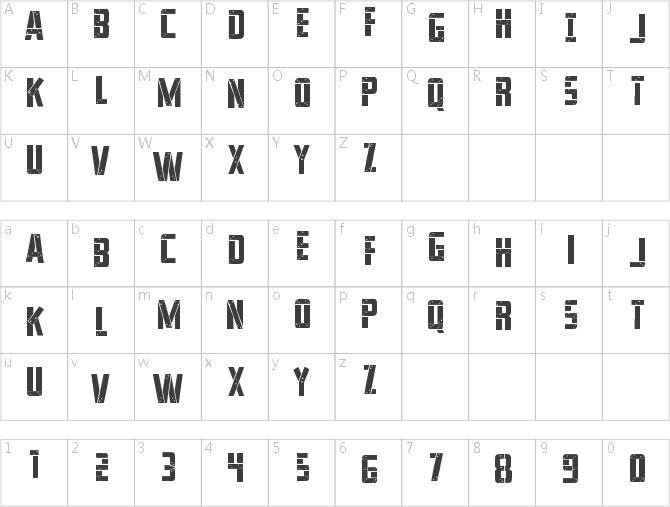
Frank-n-Plank Staggered 詳情頁
Frank-n-Plank Staggered
Frank-n-Plank Staggered介紹
Frank-n-Plank Staggered字體字庫是一款讓人賞心悅目、百看不厭的英文字體,適合各類廣告和產品包裝設計應用,字體大小0.09MB,格式為ttf字體,上傳用戶是錦程正陽,作者/版權方為未知